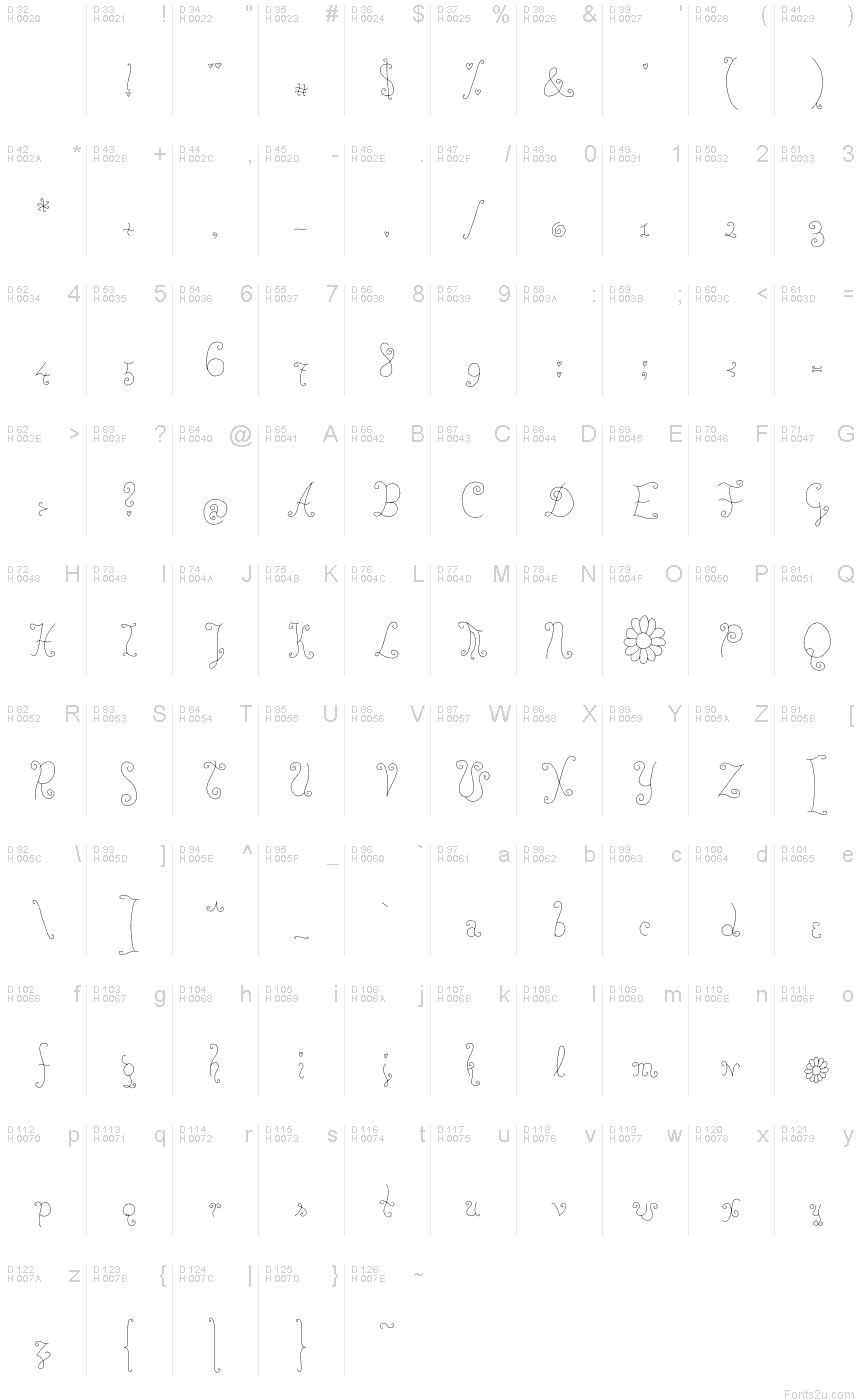
RoseWater to darmowy, kwiatowy font typu display, który zachwyca lekkością i ręcznie rysowanym charakterem przypominającym szyld butiku. Litery opierają się na długich, pętlowych pociągnięciach i miękkich spiralach, a kwiat wkomponowany w nazwę sprawia, że cały alfabet nabiera bardziej botanicznego niż tylko ozdobnego wyrazu.
Font ten świetnie sprawdzi się w papeterii ślubnej, brandingu salonów, na etykietach świec, kartkach okolicznościowych i w krótkich nagłówkach, gdzie zawijasy mają przestrzeń, by wybrzmieć. Jako darmowy font, RoseWater najlepiej prezentuje się w krótkich formach graficznych, takich jak tytuły, monogramy czy inicjały, ponieważ jego pętlowe kształty i detale przypominające płatki tworzą nastrój, który jest ważniejszy niż sam komunikat.